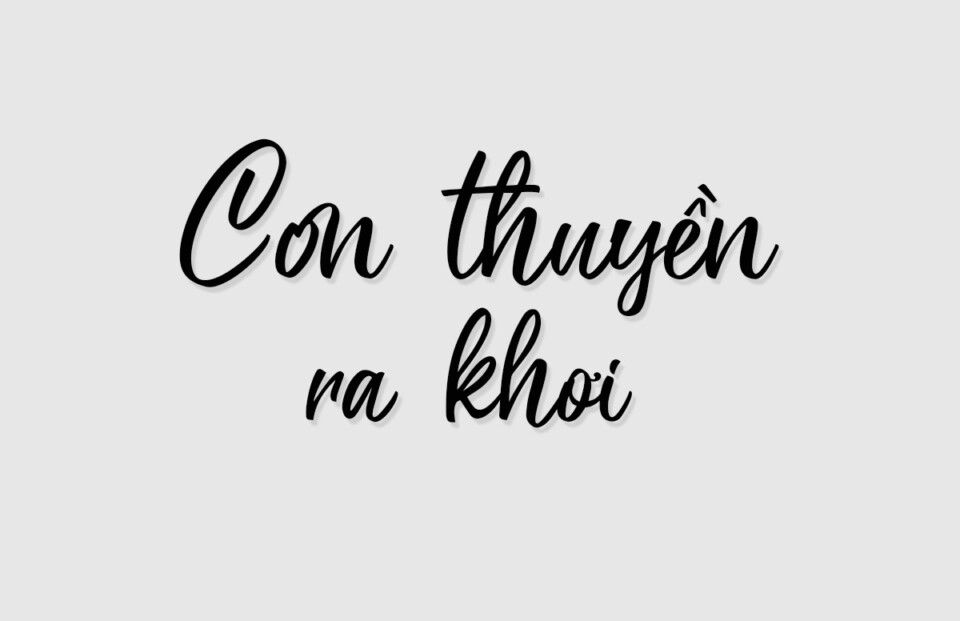
Font Việt hóa 1FTV VIP Monttee
Font Việt hóa 1FTV VIP Monttee là một trong những bộ phông chữ cao cấp được thiết kế tinh tế, mang lại vẻ đẹp hiện đại, sang trọng và đầy tính nghệ thuật cho mọi dự án đồ họa. Với việc tích hợp đầy đủ hệ thống dấu tiếng Việt chuẩn xác cùng đường nét uốn lượn chuẩn mực, bộ font này hứa hẹn sẽ trở thành công cụ đắc lực hỗ trợ các nhà thiết kế tạo nên những tác phẩm ấn tượng. Dù bạn đang làm việc trong lĩnh vực nhận diện thương hiệu, thiết kế bao bì hay các ấn phẩm truyền thông số, 1FTV VIP Monttee đều đáp ứng một cách mượt mà và chuyên nghiệp.
Font Việt hóa 1FTV VIP Monttee – Bộ Phông Chữ Đẳng Cấp Cho Thiết Kế Đồ Họa Chuyên Nghiệp
Trong kỷ nguyên sáng tạo nội dung và thiết kế đồ họa phát triển mạnh mẽ như hiện nay, việc lựa chọn một bộ phông chữ vừa đáp ứng tính thẩm mỹ cao, vừa hỗ trợ gõ tiếng Việt hoàn hảo luôn là bài toán quan trọng đối với các designer. Font Việt hóa 1FTV VIP Monttee ra đời như một giải pháp toàn diện, giải quyết triệt để vấn đề lỗi font, mất dấu hay các nét chữ bị xô lệch khi gõ tiếng Việt. Bộ phông chữ này không chỉ giữ nguyên tinh thần nghệ thuật nguyên bản của bản thiết kế gốc mà còn được căn chỉnh tỉ mỉ từng dấu thanh, dấu mũ để tạo nên sự hài hòa tuyệt đối về mặt thị giác.
Sở hữu phong cách đường nét mềm mại nhưng vẫn giữ được sự vững chãi, tính cấu trúc cao, 1FTV VIP Monttee rất phù hợp cho các tiêu đề lớn, banner quảng cáo, thiệp mời cao cấp, bộ nhận diện thương hiệu và các ấn phẩm thời trang. Việc ứng dụng bộ font VIP này sẽ giúp sản phẩm thiết kế của bạn nâng tầm giá trị, thu hút ánh nhìn của khách hàng ngay từ lần đầu tiên và truyền tải thông điệp một cách vô cùng tinh tế.
Chức Năng Và Đặc Điểm Nổi Bật Của Font 1FTV VIP Monttee
1. Tích Hợp Hệ Thống Dấu Tiếng Việt Chuẩn Xác Và Tự Nhiên
Điểm khác biệt lớn nhất của phiên bản Việt hóa 1FTV VIP Monttee chính là sự trau chuốt kỹ lưỡng trong việc bổ sung toàn bộ hệ thống dấu tiếng Việt. Các dấu thanh như sắc, huyền, hỏi, ngã, nặng cùng các dấu mũ (â, ê, ô, ơ, ư, đ) đều được thiết kế lại với tỷ lệ chuẩn xác, khoảng cách kerning được tối ưu hóa để không làm ảnh hưởng đến độ rộng và chiều cao tổng thể của dòng chữ. Nhờ đó, văn bản khi gõ ra luôn đảm bảo tính cân đối, không bị chồng chéo hay tạo cảm giác gượng gạo như các bản font Việt hóa tự động thông thường.
2. Kho Bộ Ký Tự Thay Thế (Stylistic Alternates) Và Ligatures Phong Phú
Font 1FTV VIP Monttee đi kèm với một hệ thống ký tự thay thế (Alternates) và các nét nối chữ (Ligatures) cực kỳ đa dạng chuẩn OpenType. Tính năng này cho phép các nhà thiết kế tự do sáng tạo, biến tấu các chữ cái đầu dòng hoặc các nét kết thúc thành những đường cong uốn lượn nghệ thuật. Bạn có thể dễ dàng biến một dòng chữ tiêu đề đơn giản thành một tác phẩm typography độc đáo, mang đậm tính cá nhân hóa mà không cần phải vẽ tay thủ công từng nét.
3. Tính Ứng Dụng Đa Dạng Cho Nhiều Loại Hình Thiết Kế
Với định hướng thẩm mỹ đa dụng, font chữ này không bị giới hạn trong một khuôn mẫu nhất định. 1FTV VIP Monttee thể hiện xuất sắc vai trò của mình trong nhiều mảng thiết kế khác nhau:
• Thiết kế nhận diện thương hiệu: Thích hợp làm Logo, Slogan, Card visit cho các thương hiệu thời trang, mỹ phẩm, spa, trang sức và bất động sản cao cấp.
• Ấn phẩm truyền thông & Quảng cáo: Tạo điểm nhấn mạnh mẽ cho Banner, Poster, Key Visual, Standee và hình ảnh hiển thị trên mạng xã hội (Facebook, Instagram, TikTok).
• Bao bì & Nhãn mác: Nâng cao giá trị thẩm mỹ cho bao bì sản phẩm, vỏ hộp quà tặng, chai lọ mỹ phẩm hoặc nhãn chai rượu.
•  việc của designer trở nên thuận tiện và đồng bộ hơn.
Bí Quyết Sử Dụng Font 1FTV VIP Monttee Đạt Hiệu Quả Thị Giác Tối Đa
Để phát huy hết vẻ đẹp của bộ phông chữ 1FTV VIP Monttee trong các dự án thiết kế, bạn có thể áp dụng một số quy tắc kết hợp typography sau đây:</p>
1. Khai thác tính phân cấp thị giác (Visual Hierarchy): Sử dụng 1FTV VIP Monttee làm phông chữ chủ đạo cho các tiêu đề chính (Heading 1, Title) để thu hút sự chú ý. Đối với đoạn văn bản bản tin (Body text), hãy kết hợp với một phông chữ Sans-serif đơn giản, dễ đọc như Montserrat, Helvetica hoặc Roboto để tạo sự cân bằng.
2. Tận dụng khoảng trắng (Negative Space): Do bản thân font Monttee có nhiều đường nét tinh tế và ký tự cách điệu, bạn nên dành đủ khoảng trống xung quanh khối chữ để các chi tiết nghệ thuật được nổi bật, tránh làm bố cục bị rối mắt.
3. Phối hợp màu sắc hợp lý: Phông chữ này cực kỳ hợp với các tone màu sang trọng như vàng kim (Gold), ánh bạc (Silver), đen tuyền, trắng ngà hoặc các gam màu pastel nhẹ nhàng. Việc kết hợp màu sắc đúng điệu sẽ làm tôn lên vẻ xa xỉ của bản thiết kế.
Ấn phẩm sự kiện: Tạo sự trang trọng cho thiệp cưới, thư mời sự kiện, menu nhà hàng và bìa tạp chí.